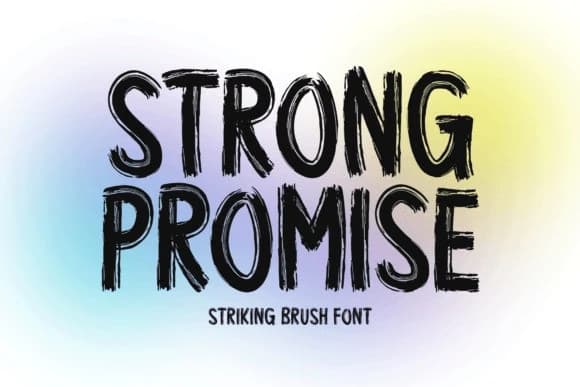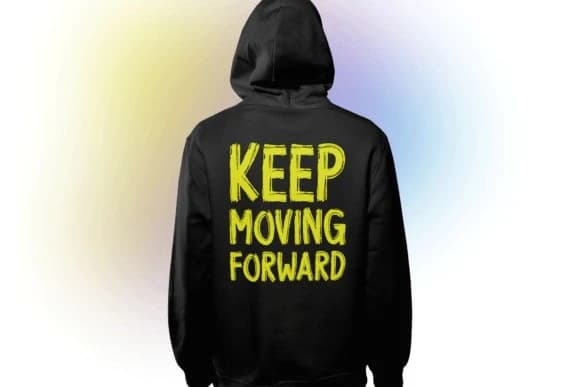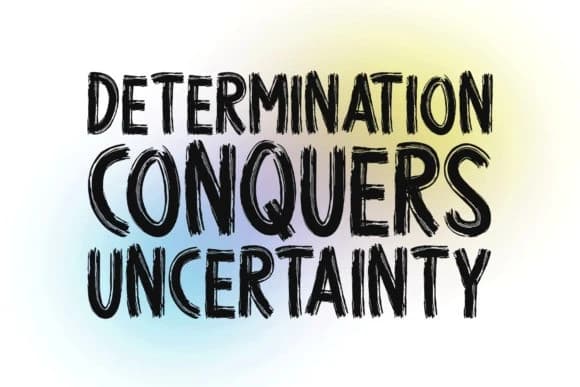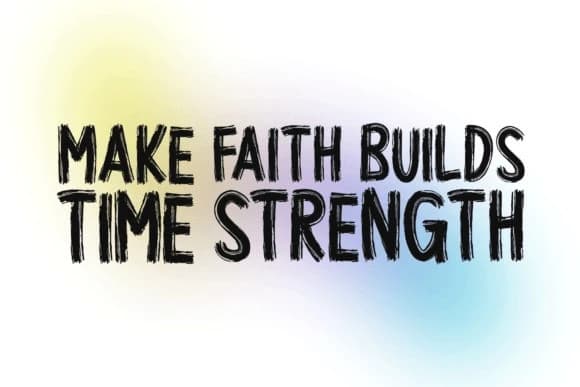
Strong Promise Font
Strong Promise font, kalın vuruşlar ve ifade dolu dokularla ustaca tasarlanmış güçlü bir fırça stilinde gösterim yazı tipidir. Projelerinizin dikkat çekmesini isteyenler için mükemmeldir—logolar, tişörtler, afişler, müzik kapakları veya dijital grafikler için.
Strong Promise yazı tipi, kalın vuruşlar ve ifade dolu dokuyla tasarlanmış güçlü bir fırça stilinde gösterim yazı tipidir. Dikkat çekmesi gereken projeler için mükemmeldir—ister logolar, tişörtler, afişler, müzik kapakları veya dijital grafikler olsun.